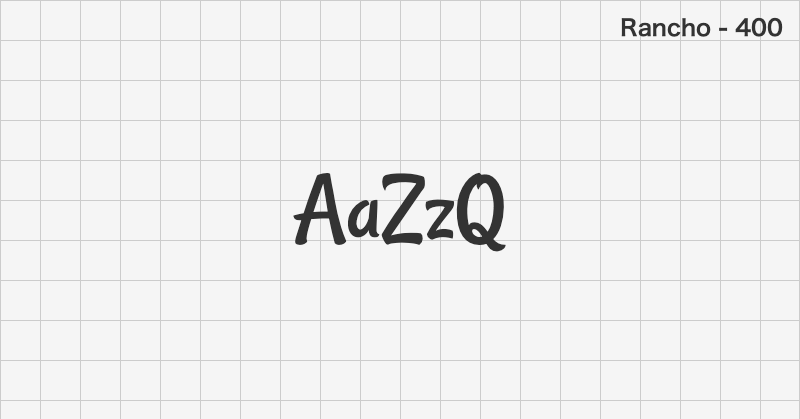
Rancho – 商用利用できる手書きフリーフォント
Rancho 手書きフォントの文字見本 (無料ダウンロード) 手書き
Rancho は、快適な筆文字フォントで、カジュアルな雰囲気を持っています。農場やカントリークラブでも使いやすいデザインです。
Rancho は、Sideshow によって開発され、カジュアルで親しみやすい印象を持つフォントとして設計されました。